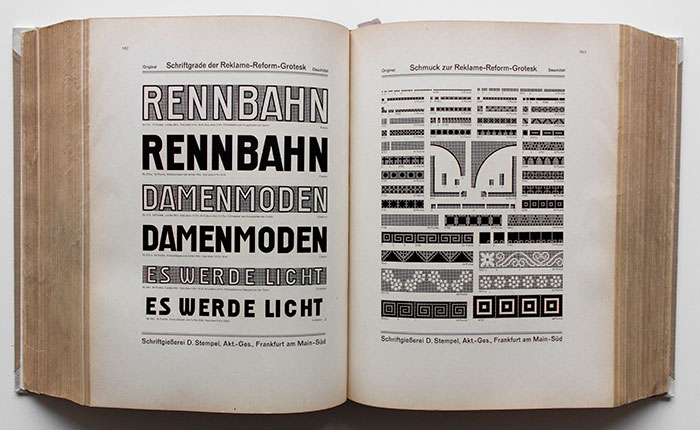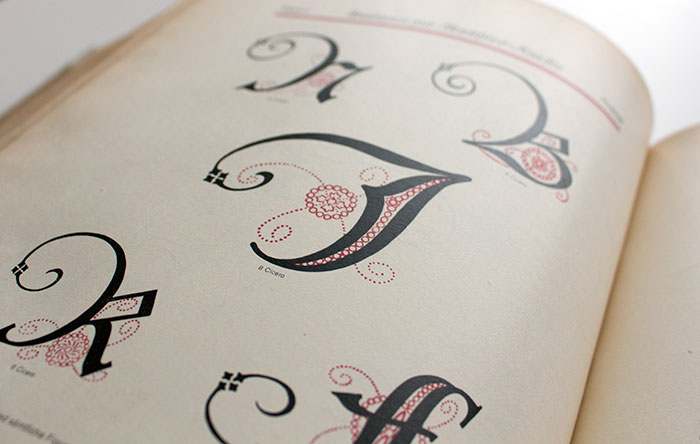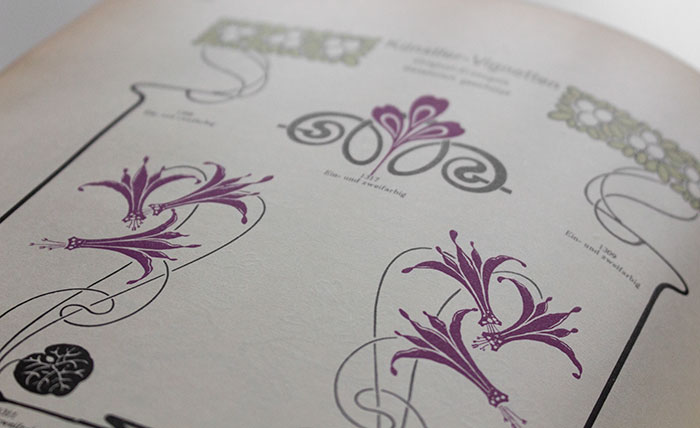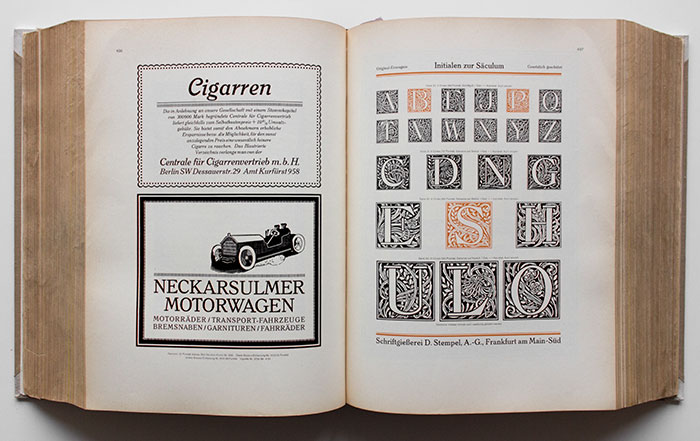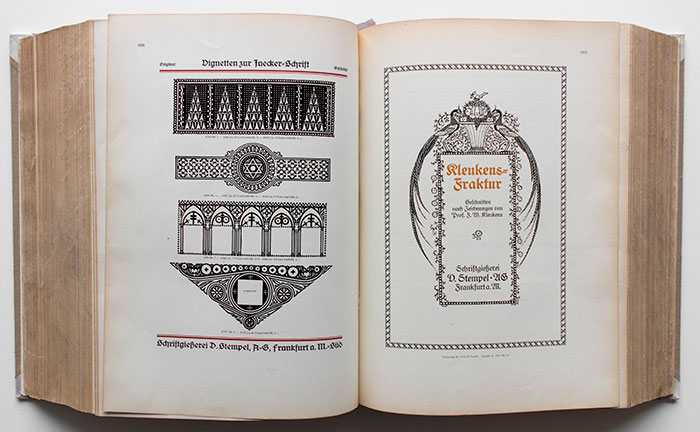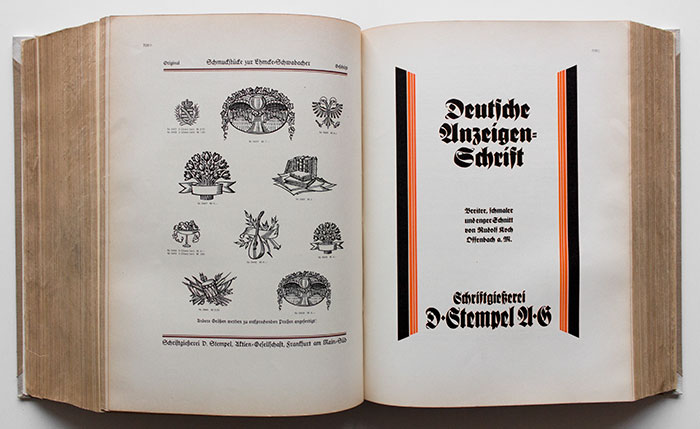
Das Ende des 19. Jahrhunderts von David Stempel gegründete Unternehmen wurde zu einer der bedeutendsten Schriftgießereien des 20. Jahrhunderts. 1925 gab das mittlerweile als Aktiengesellschaft firmierende Unternehmen eine circa 1500 Seiten starke Hauptprobe heraus. Sie ist eine der umfangreichsten Schriftproben überhaupt und ein einmaliges Spiegelbild der Typografie der Zeit. Neben häufig eingesetzten Bleisatz-Schriften zeigt die Probe auch die Einfassungen, Vignetten, Linien, Spezialziffern, Muster etc.
Inhaltsverzeichnis:
- Achilles-Fraktur
- Achilles-Fraktur, fette
- Achilles-Fraktur, halbfette
- Adler-Schreibmaschinenschrift
- Akzidenz-Gotisch, schmale
- Akzidenz-Schmuck
- Aldine, halbfette
- Aldine, schmale englische
- Altgotisch, Amerikanische
- Altgotisch, enge
- Altgotisch, Original-
- Altgotisch, Original-, Anwendung
- Alt-Schwabacher
- Alt-Schwabacher, Anwendung
- Amts-Antiqua
- Amts-Antiqua, Anwendung
- Amts-Antiqua, enge
- Amts-Antiqua, enge halbfette
- Amts-Antiqua, fette
- Amts-Antiqua, halbfette
- Amts-Fraktur
- Amts-Fraktur, Anwendung
- Amts-Fraktur, enge halbfette
- Amts-Fraktur, fette
- Amts-Fraktur, halbfette
- Amts-Fraktur-Initialen
- Amts-Fraktur, magere
- Amts-Fraktur, magere, Anwendung
- Amts-Fraktur, schmale fette
- Amts-Kursiv
- Amts-Kursiv, halbfette
- Amts-Kursiv, fette
- Amts-Schriften
- Amts-Schriften-ZIffern
- Ancienne
- Antike Elzevier
- Antike Elzevier, Anwendung
- Antike Skelett
- Antiqua-Brotschriften
- Antiqua, halbfette englische
- Antiqua, moderne fette
- Antiqua, Salon-
- Antiqua, Salon-, Anwendung
- Antiqua, schmale schlanke
- Antiqua, schmale halbfette
- Antiqua, schraffierte
- Anzeigenschrift
- Arabische Schriften
- Ariadne-Fraktur
- Ariadne-Fraktur, halbfette
- Aristokrat
- Aristokrat, Anwendung
- Armenische Schriften
- Arminius-Fraktur
- Arminius-Fraktur, halbfette
- Askpekten-Zeichen
- Astronomische Zeichen
- Assüree-Linien
- Assüree-Linien mit Wertzeichen und Firmenzeile
- Ausläufer für Messinglinien
- Auszeichnungsschriften für Brotschriften
- Barnum-Ornamente
- Baskerville, Original-, Anwendung
- Bek-Gran
- Bek-Gran-Einfassungen
- Bek-Gran-Einfassungen zweifarbig
- Bek-Gran, halbfette
- Bek-Gran-Initial-Verzierungen
- Bek-Gran-Kalender-Vignetten
- Bek-Gran-Schrift, Anwendung
- Bek-Gran-Umrahmungen
- Bek-Gran-Vignetten
- Bek-Gran, Werk-
- Berg- und Hüttenzeichen
- Bewegte Messinglinien mit Ecken
- Biedermeier-Reklame
- Biedermeier-Schmuck
- Blattstab, lichter und fetter
- Blumenschmuck Flora
- Blumenzauber-Einfassung
- Bogenregletten in Messing
- Börsenkurs-Schriften
- Börsenkurs-Schriften, Anwendung
- Börsenkurs-Zeichen
- Börsenkurs-Ziffern
- Bravour, Anwendung
- Bravour-Einfassung in Messing
- Bravour, fette
- Bravour, halbfette
- Bravour-Kursiv, fette
- Bravour-Kursiv, magere
- Bravour, magere
- Bravour, schmale fette
- Bravour, schmale magere
- Bravour-Schmuck
- Bravour, schraffierte
- Bravour, verzierte
- Bravour-Vignetten
- Bravour-Ziffern
- Breite Etienne
- Breite fette Egyptienne
- Breite fette Grotesk
- Breite Gotisch
- Breite Grotesk
- Breite fette Reform-Grotesk
- Breite fette Reform-Grotesk-Versalien
- Breite fette Renaissance
- Breite fette Salon-Grotesk
- Breite halbfette Reform-Grotesk
- Breite halbfette Reform-Grotesk-Versalien
- Breite halbfette Reform-Grotesk II
- Breite halbfette Reform-Grotesk II-Versalien
- Breite halbfette Renaissance
- Breite halbfette Salon-Grotesk
- Breite Inseraten-Reform-Grotesk
- Breite Inseraten-Reform-Grotesk-Versalien
- Breite Offenbacher Schwabacher
- Breite verzierte Italienne
- Breitkopf-Fraktur
- Breitkopf-Fraktur, Anwendung
- Breitkopf-Fraktur, halbfette
- Brotschriften, Kolonel mit großem Schriftbild
- Brotschriften, Insertio
- Brotschriften, Nonp. mit großem Schriftbild
- Brotschriften, Petit mit großem Schriftbild
- Bruchziffern
- Bruchziffern für Börsenkurse
- Buchgotisch
- Buchgotisch, Anwendung
- Buchgotisch, fette
- Buchgotisch, halbfette
- Buchgotisch, Initialen
- Buchgotisch, Schmuck
- Buhe-Fraktur
- Buhe-Fraktur, Anwendung
- Buhe-Fraktur, fette
- Buhe-Fraktur, fette, Anwendung
- Buhe-Fraktur, halbfette
- Buhe-Initialen
- Buhe-Schmuck
- Bürck-Linien
- Bürck-Schrift
- Bürck-Schrift, Anwendung
- Büxenstein-Antiqua
- Büxenstein-Antiqua, Anwendung
- Büxenstein-Antiqua, halbfette
- Büxenstein-Fraktur
- Büxenstein-Fraktur, Anwendung
- Büxenstein-Fraktur, halbfette
- Büxenstein-Kursiv
- Caslon-Gotisch
- Caslon-Gotisch, Anwendung
- Ceres-Fraktur
- Ceres-Fraktur, Anwendung
- Ceres-Fraktur, halbfette
- Christiansen-Einfassungen
- Christiansen-Intitialen
- Christiansen-Schrift
- Christiansen-Schrift, Anwendung
- Christiansen-Vignetten
- Clarendon
- Colonel-Brotschriften mit großem Schriftbild
- Continental
- Cyrillische Amts-Antiqua-Schriften
- Cyrillische Bravour-Schriften
- Cyrillische Holz-Schriften
- Cyrillische Karten-Schriften
- Cyrillische Reform-Grotesk-Schriften
- Cyrillische Römisch-Schriften
- Cyrillische Säculum-Schriften
- Cyrillische Schreibmaschinen-Schriften
- Damespiel-Figuren
- Danziger Antiqua
- Danziger Fraktur
- Danziger Fraktur, fette
- Delphin-Antiqua
- Delphin-Antiqua, halbfette
- Delphine-Kursiv
- Deutsche Anzeigenschrift, Anwendung
- Deutsche Anzeigenschrift, breiter Schnitt
- Deutsche Anzeigenschrift, enger Schnitt
- Deutsche Anzeigenschrift, Initialen
- Deutsche Anzeigenschrift, Schlußzeichen
- Deutsche Anzeigenschrift, schmaler Schnitt
- Deutsche Anzeigenschrift, Schwungbuchstaben
- Deutsche Handschreibschrift
- Deutsche Laufschrift
- Deutsche Laufschrift, Anwendung
- Deutsche Laufschrift, Endbuchstaben
- Deutsche Laufschrift-Initialen
- Deutsche Laufschrift, Zeilenfüller
- Deutsche Schreibschrift
- Deutsche Spielkartentypen
- Deutsche Zierschrift
- Diana
- Diana, Anwendung
- Diana, halbfette
- Didot-Antiqua
- Didot-Antiqua-, Anwendung
- Didot-Kursiv
- Dominospiel-Figuren
- Dreiviertelfette Reform-Grotesk
- Dreiviertefette Reform-Grotesk-Versalien
- Dutzend-Zeichen
- Egmont-Fraktur
- Egmont-Fraktur, Anwendung
- Egmont-Fraktur, fette
- Egmont-Fraktur, halbfette
- Egyptienne, breite fette
- Egyptienne-Kursiv, fette
- Egyptienne, magere enge
- Egyptienne, schmale
- Ehmcke-Fraktur
- Ehmcke-Fraktur, Anwendung
- Ehmcke-Fraktur, halbfette
- Ehmcke-Fraktur-Intitialen
- Ehmcke-Mediaeval
- Ehmcke-Medieaval, Anwendung
- Ehmcke-Mediaeval, halbfette
- Ehmcke-Mediaeval-Initialen
- Ehmcke-Mediaeval-Kursiv
- Ehmcke-Mediaeval-Schmuck
- Ehmcke-Mediaeval-Tabellen-Ziffern
- Ehmcke-Rustika
- Ehmcke-Rustika, Anwendung
- Ehmcke-Rustika-Initialen
- Ehmcke-Rustika-Schmuck
- Ehmcke-Schwabacher
- Ehmcke-Schwabacher, Anwendung
- Ehmcke-Schwabacher, halbfette
- Ehmcke-Schwabacher-Schmuck
- Ehmcke-Schwabacher-Schmuckstücke
- Ehmcke-Schwabacher-Zierbuchstaben
- Einfassung Herkules
- Einfassung Heureka
- Einfassung Immer fertig
- Einfassung Lätizia
- Einfassung Merkuria
- Einfassung Modern
- Einfassung Nestor
- Einfassung Non plus ultra
- Einfassung Orion
- Einfassung Propaganda
- Einfassung Serie 32
- Einfassung Serie 33
- Einfassung Serie 34
- Einfassung Serie 40
- Einfassung Serie 41
- Einfassung Serie 42
- Einfassung Serie 43
- Einfassung Serie 44
- Einfassung Serie 45
- Einfassung Serie 48
- Einfassung Serie 50
- Einfassung Serie 51
- Einfassung Solitair
- Einfassung Viktoria
- Einfassungen in Holz
- Einfassungen in Messing
- Einfassungen, mehrfarbige
- Einfassungen, Nachtrag zu den Reihen-
- Einfassungen, Reihen-
- Einfassungen zur Bek-Grau
- Einfassungen zur Bek-Grau, zweifarbig
- Einfassungen zur Bravour
- Einfassungen zur Buhe Fraktur
- Einfassungen zur Christiansen-Schrift
- Einfassungen zur Ehmcke-Mediaeval
- Einfassungen zur Ehmcke-Rustika
- Einfassungen zur Ehmcke-Schwabacher
- Einfassungen zur Frankfurt-Serie
- Einfassungen zur Gotischen Antiqua
- Einfassungen zur Helga-Antiqua
- Einfassungen zur Hölzl-Mediaeval
- Einfassungen zur Ingeborg-Antiqua
- Einfassungen zur Jaecker-Schrift
- Einfassungen zur Kleukens-Fraktur
- Einfassungen zur Matthies-Kursiv
- Einfassungen zur Reklame-Reform-Grotesk
- Einfassungen zur Sensation
- Einfassungs-Linien in Messing
- Einheits-Fraktur
- Ekkehard-Fraktur
- Ekkehard-Fraktur, Anwendung
- Ekkehard-Fraktur, halbfette
- Elegant
- Elegant, Anwendung
- Elfen-Fraktur
- Elfen-Fraktur, Anwendung
- Elfen-Fraktur-Initialen
- Elite-Kanzlei
- Elite-Kanzlei, Anwendung
- Elite, Zierschrift
- Elzevier, antike
- Elzevier, antike, Anwendung
- Endbuchstaben zur Deutschen Laufschrift
- Enge Altgotisch
- Enge Amts-Antiqua
- Enge Amts-Antiqua, Anwendung
- Enge Etienne
- Enge Etienne, Anwendung
- Enge fette Reform-Grotesk
- Enge fette Reform-Grotesk-Versalien
- Enge halbfette Reform-Grotesk
- Enge halbfette Reform-Grotesk-Versalien
- Enge halbfette Amts-Antiqua
- Enge halbfette Amts-Fraktur
- Enge Jaecker-Schrift
- Enge moderne Kanzlei
- Enge Normannia-Fraktur
- Enge Normannia-Fraktur, halbfette
- Enge magere Reform-Grotesk
- Enge magere Reform-Grotesk-Versalien
- Enge magere Säculum
- Enge Renaissance
- Englische Aldine, schmale
- Englische Antiqua, halbfette
- Englische Messinglinien
- Erator-Antiqua
- Erato-Kursiv
- Etienne, breite
- Etienne, enge
- Etienne, enge, Anwendung
- Etienne, freie
- Etienne, lichte
- Etienne, schmale fette
- Fahrplan-Anwendung
- Fahrplan-Material
- Fahrplan-Ziffern
- Fakturen-Zeihen
- Falstaff
- Faust-Fraktur
- Faust-Fraktur, Anwendung
- Faust-Fraktur, halbfette
- Faust-Fraktur, fette
- Faust-Fraktur, schmale halbfette
- Federzüge zur Jaecker-Schrift
- Fenella-Fraktur
- Fenella-Fraktur, Anwendung
- Fenelle-Fraktur, halbfette
- Feodora, Schreibschrift
- Fette Achilles-Fraktur
- Fette Amts-Antiqua
- Fette Amts-Fraktur
- Fette Amts-Kursiv
- Fette Antiqua, grobe Kolonel
- Fette Antiqua, grobe Petit
- Fette Antiqua, moderne
- Fette Bravour
- Fette Bravour-Kursiv
- Fette Buchgotisch
- Fette Buhe-Fraktur
- Fette Buhe-Fraktur, Anwendung
- Fette Ceres-Fraktur
- Fette Egmont-Fraktur
- Fette Egyptienne-Kursiv
- Fette Faust-Fraktur
- Fette Fraktur
- Fette Gotisch
- Fette Graziella
- Fette Grazielle, Anwendung
- Fette Gutenberg-Jubiläums-Fraktur
- Fette klassische Ornamente Serie 21
- Fette König-Antiqua
- Fette Kursiv
- Fette Normannia-Fraktur
- Fette Offenbacher Schwabacher
- Fette Reform-Grotesk
- Fette Reform-Grotesk-Versalien
- Fette Reform-Grotesk-Kursiv
- Fette Reform-Grotesk-Kursiv-Versalien
- Fette Regina-Kursiv
- Fette Regina-Kursiv, Anwendung
- Fette Säculum
- Fette Schiller-Jubiläumsschrift
- Fette Schiller-Jubiläumsschrift, Anwendung
- Fette Schwabacher
- Fette Sensation
- Fette Teutonia
- Fette Torpedo
- Fette Undine
- Fetter Blattstab
- Fortschritt-Schmuck
- Fraktur-Brotschriften
- Fraktur, fette
- Fraktur, halbfette
- Fraktur-Initialen
- Fraktur-Initialen, kräftige
- Fraktur, schmale halbfette
- Frankfurt-Schrift, Anwendung
- Frankfurt-Serie I
- Frankfurt-Serie II
- Frankfurt-Serie I und II, Anwendung
- Frankfurt-Serie, Initialen zur
- Frankfurt-Serie, Kopfleisten zur
- Frankfurt-Serie, Ornamente zur
- Frankfurter Schwabacher
- Frankfurter Schwabacher, halbfette
- Französische Spielkartentypen
- Freie Etienne
- Freie Grotesk I
- Freie Grotesk II
- Freie Initialen zur Kleukens-Fraktur
- Freie Korso-Versalien
- Freie Ornamente, moderne
- Freie Romanisch
- Freie Versalien zur Kleukens-Fraktur
- Freie Versalien zur Matthias-Kursiv
- Freie Versalien zur Ratio-Latein
- Fröbel-Fraktur
- Fröbel-Fraktur, halbfette
- Frühling
- Garamond-Antiqua, Anwendung
- Germinal
- Gewichtszeichen
- Gotische Antiqua
- Gotische Antiqua, Anwendung
- Gotische Antiqua-Einfassungen
- Gotische Antiqua-Initialen
- Gotisch, breite
- Gotisch, Caslon
- Gotisch, fette
- Gotisch, Kaiser-
- Gotisch, Morris-
- Gotisch, schmale Akzidenz
- Gotisch, schmale halbfette
- Graphik
- Graziella, Anwendung
- Graziella, fette
- Graziella, magere
- Graziella, schmale fette
- Gretchen-Einfassung
- Griechische Schriften
- Grotesk, breite
- Grotesk, breite fette
- Grotesk, breite fette Salon-
- Grotesk, breite halbfette Salon-
- Grotesk, halbfette Kursiv-
- Grotesk, Handels-
- Grotesk, Handels-, Anwendung
- Grotesk I und II, freie
- Grotesk, Inseraten-
- Grotesk, magere schlanke
- Grotesk, Mediaeval-
- Grotesk, neue schlanke
- Grotesk, Reform, siehe Reform-Grotesk
- Grotesk, Siegfried-
- Grotesk, schlanke
- Grotesk, schmale enge
- Grotesk, schmale halbfette
- Gutenberg-Fraktur
- Gutenberg-Jubiläums-Fraktur
- Gutenberg-Jubiläums-Fraktur, Anwendung
- Gutenberg-Jubiläums-Fraktur, fette
- Gutenberg-Jubiläums-Fraktur, halbfette
- Halbfette Achilles-Fraktur
- Halbfette Aldine
- Halbfette Amts-Antiqua
- Halbfette Amts-Fraktur
- Halbfette Amts-Kursiv
- Halbfette Arminus-Fraktur
- Halbfette Ariadne-Fraktur
- Halbfette Bek-Gran
- Halbfette Bravour
- Halbfette Breitkopf-Fraktur
- Halbfette Buhe-Fraktur
- Halbfette Buchgotisch
- Halbfette Büxenstein-Antiqua
- Halbfette Büxenstein-Fraktur
- Halbfette Ceres-Fraktur
- Halbfette Danziger-Fraktur
- Halbfette Delphin-Antiqua
- Halbfette Diana
- Halbfette englische Antiqua
- Halbfette Egmont-Fraktur
- Halbfette Ehmcke-Fraktur
- Halbfette Ehmcke-Mediaeval
- Halbfette Ehmcke-Schwabacher
- Halbfette Ekkehard-Fraktur
- Halbfette Faust-Fraktur
- Halbfette Fenelle-Fraktur
- Halbfette Fraktur
- Halbfette Frankfurter Schwabacher
- Halbfette Fröbel-Fraktur
- Halbfette Gutenberg-Jubiläums-Fraktur
- Halbfette Heinz-König-Setzmaschinen-Fraktur
- Halbfette Helga-Antiqua
- Halbfette Helvetia
- Halbfette Holländische Antiqua
- Halbfette Holzhausen-Antiqua
- Halbfette Hölzl-Mediaeval
- Halbfette Ingeborg-Antiqua
- Halbfette Jaecker-Schrift
- Halbfette Kanzlei
- Halbfette Kleukens-Fraktur
- Halbfette Kursiv
- Halbfette Kursiv-Grotesk
- Halbfette Künstlerschrift
- Halbfette Künstler-Schreibschrift
- Halbfette Labor-Antiqua
- Halbfette Marius-Fraktur
- Halbfette Mediaeval I
- Halbfette Medieaval I, Anwendung
- Halbfette Mediaeval II
- Halbfette Mediaeval-Schreibschrift
- Halbfette Merkur
- Halbfette moderne Schwabacher
- Halbfette Neuklassisch
- Halbfette Neuzeit-Antiqua
- Halbfette Neuzeit-Fraktur
- Halbfette Normannia-Fraktur
- Halbfette Offenbacher Schwabacher
- Halbfette Perfekt
- Halbfette Perikles-Antiqua
- Halbfette Ratio-Latein
- Halbfette Reform-Antiqua
- Halbfette Reform-Fraktur
- Halbfette Reform-Grotesk
- Halbfette Reform-Grotesk-Versalien
- Halbfette Reform-Grotesk-Kursiv
- Halbfette Reform-Grotesk-Kursiv-Versalien
- Halbfette Renaissance
- Halbfette Romanisch
- Halbfette Romanisch-Kursiv
- Halbfette Romeo-Fraktur
- Halbfette Romulus-Fraktur
- Halbfette Römisch
- Halbfette Römisch-Kursiv
- Halbfette Säculum
- Halbfette Säculum-Kursiv
- Halbfette Schreibschrift
- Halbfette Schwabacher
- Halbfette Setzmaschinen-Mediaeval
- Halbfette Setzmaschinen-Romanisch
- Halbfette Städel-Antiqua
- Halbfette Stempel-Fraktur
- Halbfette Turnus-Antiqua
- Halbfette Union
- Halbfette Weißflog-Antiqua
- Halbfette Wiener Antiqua
- Handels-Antiqua
- Handels-Grotesk
- Handels-Grotesk, Anwendung
- Handschreibschrift, deutsche
- Handschreibschrift, lateinische
- Hände
- Hände in Holz
- Hände in Messing
- Hebräische Schriften
- Heinz König-Setzmaschinen-Fraktur
- Heinz König-Setzmaschinen-Fraktur, Andwendung
- Heinz König-Setzmaschinen-Fraktur, halbfette
- Helga-Antiqua
- Helga-Antiqua, Anwendung
- Helga-Antiqua, halbfette
- Helga-Einfassungen
- Helga-Initialen
- Helga-Kursiv
- Helga-Vignetten
- Helvetia, halbfette
- Helvetia, magere
- Herkules-Einfassung
- Herold
- Heureka-Einfassung
- Holländische Antiqua
- Holländische Antiqua, halbfette
- Holländische Antiqua-Initialen
- Holländische Kursiv
- Holzhausen-Antiqua
- Holzhausen-Antiqua, Anwendung
- Holzhausen-Antiqua, halbfette
- Holzhausen-Kursiv
- Holzschriften
- Hölzl-Medieaeval, Anwendung
- Hölzl-Medieaeval, halbfette
- Hölzl-Medieaeval-Initialen
- Hölzl-Medieaeval-Kursiv
- Hölzl-Medieaeval-Ornamente
- Hölzl-Medieaeval-Vignetten
- Hölzl-Medieaeval-Ziffern
- Hubertus-Fraktur, I. und II. Garnitur
- Hütten-Zeichen
- Immer fertig, Einfassung
- Ingeborg-Antiqua
- Ingeborg-Antiqua, Anwendung
- Ingeborg-Antiqua, halbfette
- Ingeborg-Antiqua-Ziffern
- Ingeborg-Initialen
- Ingeborg-Kursiv
- Ingeborg-Ornamente
- Ingeborg-Vignetten
- Initial-Kassetten zur Matthies-Kursiv
- Initial-Verzierungen zur Bek-Gran
- Initialen, Fraktur-
- Initialen, kräftige Fraktur-
- Initialen zur Amts-Fraktur
- Initialen zur Buhe-Fraktur
- Initialen zur Buchgotisch
- Initialen zur Christiansen-Schrift
- Initialen zur Deutschen Anzeigenschrift
- Initialen zur Deutschen Laufschrift
- Initialen zur Ehmcke-Fraktur
- Initialen zur Ehmcke-Mediaeval
- Initialen zur Ehmcke-Rustika
- Initialen zur Ehmcke-Schwabacher
- Initialen zur Elfen-Fraktur
- Initialen zur Frankfurt-Serie
- Initialen zur Gotischen Antiqua
- Initialen zur Helga-Antiqua
- Initialen zur Holländischen Antiqua
- Initialen zur Hölzl-Mediaeval
- Initialen zur Ingeborg-Antiqua
- Initialen zur Jaecker-Schrift
- Initialen zur Kleukens-Fraktur
- Initialen zur Künstlerschrift
- Initialen zur Matthies-Kursiv
- Initialen zur modernen Schwabacher
- Initialen zur Morris-Gotisch
- Initialen zur Neuzeit-Antiqua
- Initialen zur Neuzeit-Fraktur
- Initialen zur Ratio-Latein
- Initialen zur Romanisch
- Initialen zur Säculum
- Initialen zur Sensation
- Initialen zur Stempel-Fraktur
- Initialen zur Teutonia
- Inserat-Einfassungen für Handel und Gewerbe
- Inseraten-Grotesk
- Inseraten-Reform-Grotesk-Kursiv
- Inseraten-Reform-Grotesk-Kursiv-Versalien
- Insertio-Schriften
- Isabella
- Italienne
- Italienne, breite verzierte
- Italienne, Skelett-
- Italienne, verzierte
- Integral-Zeichen
- Jaecker-Initialen
- Jaecker-Ornamente
- Jaecker-Schrift
- Jaecker-Schriftn, Anwendung
- Jaecker-Schrift, enge
- Jaecker-Schrift, halbfette
- Jaecker-Schrift, magere
- Jaecker-Schrift, magere, Anwendung
- Jaecker-Vignetten
- Jaecker-Zierat
- Janson-Antiqua
- Janson-Antiqua, Anwendung
- Janson-Kursiv
- Kaiser-Gotisch
- Kalender-Vignetten, Bek-Gran
- Kalender-Ziffern
- Kalender-Ziffern in Holz
- Kanzlei, brei
- Kanzlei, Elite-
- Kanzlei, Elite-, Anwendung
- Kanzlei, enge moderne
- Kanzlei, halbfette
- Kanzlei, Viktoria-
- Kapitälchen zur Säculum
- Kapitälchen zur Weißfloß-Antiqua
- Karolus-Fraktur
- Kartographische Zeichen
- Kassetten in Messing
- Katalog-Ziffern
- Klammern in Messing
- Klassische Ornamente Serie 21, fette
- Klassische Ornamente Serie 22
- Kleukens-Fraktur
- Kleukens-Fraktur, Anwendung
- Kleukens-Fraktur, frei Initialen
- Kleukens-Fraktur, freie Versalien
- Kleukens-Fraktur, halbfette
- Kleukens-Fraktur-Initialen
- Kleukens-Fraktur-Ornamente
- Kleukens-Vignetten
- Kolli-Zeichen
- Kolonel-Brotschriften mit großem Schriftbild
- Kolumnentitel in Messing
- Kombinationsschmuck in Messing
- Kontrast-Ornamente
- König-Antiqua
- König-Antiqua, fette
- Kopfleisten zur Frankfurt-Serie
- Kopfleisten zur Säculum
- Korrespondenz-Zeichen
- Korso
- Korso, Anwendung
- Korso, freie Versalien
- Korso-Ornamente
- Kräftige Fraktur-Initialen
- Kreise in Messing
- Kreuze
- Kreuze in Messing
- Kronen
- Kursiv, fette
- Kursiv, halbfette
- Kursiv-Grotesk, halbfette
- Kursiv-Rundschrift
- Künstler-Reform-Grotesk
- Künstlerschrift, halbfette
- Künstlerschrift-Initialen
- Künstlerschrift, lichte
- Künstlerschrift, magere
- Künstlerschrift Wodan, schmale fette
- Künstlerschrift Wodan, schmale fette, Anwendung
- Künstler-Schreibschrift
- Künstler-Schreibschrift, Anwendung
- Künstler-Schreibschrift, halbfette
- Künstler-Schreibschrift, schmale
- Künstler-Schreibschrift, schmale, Anwendung
- Künstler-Linien Serie 1
- Künstler-Linien Serie 2
- Künstler-Linien Serie 3
- Künstler-Linien Serie 4
- Künstler-Linien Serie 5
- Künstler-Linien Serie 6
- Künstler-Linien Serie 7
- Künstler-Linien Serie 8, lichte
- Künstler-Linien Serie 9
- Künstler-Linien Serie 10
- Künstler-Linien Serie 11, lichte
- Künstler-Linien Serie 12
- Künstler-Linien Serie 13
- Künstler-Vignetten
- Labor-Antiqua, Anwendung
- Labor-Antiqua, halbfette
- Lateinische Handschreibschrift
- Lätizia-Einfassung
- Libelle, Renaissance-Schrift
- Libelle, Renaissance-Schrift, Anwendung
- Lichte Etienne
- Lichte Künstlerschrift
- Lichte Künstlerlinien Serie 8
- Lichte Künstlerlinien Serie 11
- Lichte Mignon
- Lichte Ratio-Versalien
- Lichte Reform-Grotesk
- Lichte Romanisch
- Lichte schmale Renaissance
- Lichte schmale Renaissance, Anwendung
- Lichte Torpedo
- Lichte Wodan
- Lichter Blattstab
- Linien-Ausläufer in Messing
- Lithographia
- Lithographia II
- Lithographia-Versalien II
- Liturgisch
- Lotterie-Ziffern
- Luthersche Fraktur
- Luthersche Fraktur, Anwendung
- Magere Amts-Fraktur
- Magere Bravour
- Magere Bravour-Kursiv
- Magere enge Egyptienne
- Magere Graziella
- Magere Graziella, Anwendung
- Magere Helvetia
- Magere Jaecker-Schrift
- Magere Jaecker-Schrift, Anwendung
- Magere Künstlerschrift
- Magere moderne Reklame
- Magere Reform-Grotesk
- Magere Reform-Grotesk-Versalien
- Magere Reform-Grotesk-Kursiv
- Magere Reform-Grotesk-Kursiv-Versalien
- Magere Regina-Kursiv
- Magere Regina-Kursiv, Anwendung
- Magere Römisch
- Magere Römisch, Anwendung
- Magere Säculum
- Magere Schiller-Jubiläumsschrift
- Magere Schiller-Jubiläumsschrift, Anwendung
- Magere schlanke Grotesk
- Magere Undine
- Magnet
- Marie Antoinette
- Marie Antoinette, Anwendung
- Marius-Fraktur
- Marius-Fraktur, halbfette
- Mathematische Zeichen
- Matthies-Kursiv
- Matthies-Kursiv, Anwendung
- Matthies-Kursiv-Einfassungen
- Matthies-Kursiv, freie Versalien
- Matthies-Kursiv-Initialen und Initial-Kass.
- Matthies-Kursiv-Vignetten
- Maysche Fraktur I. und II. Garnitur
- Mediaeval-Grotesk
- Mediaeval I
- Mediaeval I, halbfette
- Mediaeval I, halbfette, Anwendung
- Mediaeval I, Setzmaschinen-
- Mediaeval I, Setzmaschinen-, halbfette
- Mediaeval II
- Mediaeval II, halbfette
- Mediaeval-Kursiv I
- Mediaeval-Kursiv I, Setzmaschinen-
- Mediaeval-Kursiv II
- Mediaeval, schattierte
- Mediaeval-Schreibschrift
- Mediaeval-Schreibschrift, halbfette
- Mehrfarbige Einfassungen
- Merkur
- Merkur, halbfette
- Merkuria-Einfassung
- Messing-Assüree-Linien
- Messing-Bogenregletten
- Messing-Ecken und -Mittelstücke
- Messing-Ecken, verzierte
- Messing-Einfassung Kosmos
- Messing-Einfassung Non plus ultra
- Messing-Einfassung Stabil
- Messing-Einfassungen
- Messing-Einfassungs-Linien
- Messing-Hände
- Messing-Kassetten
- Messing-Klammern
- Messing-Kolumnentitel
- Messing-Kombinations-Schmuck
- Messing-Kreise
- Messing-Kreuze
- Messing-Linien
- Messing-Linien-Ausläufer
- Messing-Linien, bewegte, mit Ecken
- Messing-Linien, englische
- Messing-Linien, Universal-
- Messing-Moiré-Linien
- Messing-Negative
- Messing-Ovale
- Messing-Pfeile
- Messing-Rubrikzeichen
- Messing-Schlußlinien
- Messing-Spaltenlinien und -Facetten
- Messing-Trauerränder
- Meteorologische Zeichen
- Metrische Zeichen
- Mignon, lichte
- Mithras-Schmuckserie
- Moderne freie Ornamente
- Moderne Plakat-Einfassung
- Moderne Reihen-Einfassungen
- Moderne Reklame
- Moderne Reklame, magere
- Moderne Schwabacher
- Moderne Schwabacher, halbfette
- Moderne Schwabacher-Initialen
- Moderne Vignetten für Prospekte, Inserate etc.
- Moiré-Linien
- Mondphasen
- Monogramme
- Morris-Gotisch
- Morris-Gotisch-Initialen
- Naturwissenschaftliche Zeichen
- Negative in Messing
- Nestor-Einfassung
- Neue Inserat-Einfass. für Hand und Gewerbe
- Neue schlanke Grotesk
- Neue zarte Säculum
- Neue zarte Säculum, Anwendung
- Neue zarte Säculum-Kursiv
- Neueste Schreibschrift
- Neuklassisch
- Neuklassisch, Anwendung
- Neuklassisch, halbfette
- Neuklassisch-Kursiv
- Neuzeit-Antiqua
- Neuzeit-Fraktur, Anwendung
- Neuzeit-Fraktur, halbfette
- Neuzeit-Fraktur-Initialen
- Neuzeit-Initialen
- Neuzeit-Kursiv
- Neuzeit-Zirkular
- Non plus ultra-Einfassung
- Nonpareille-Brotschriften mit großem Schriftbild
- Normalbreite fette Reform-Grotesk
- Normalbreite fette Reform-Grotesk-Versalien
- Normalbreite halbfette Reform-Grotesk
- Normalbreite halbfette Reform-Grotesk-Versalien
- Normalbreite Inseraten-Reform-Grotesk
- Normalbreite Inseraten-Reform-Grotesk-Versalien
- Normalbreite magere Reform-Grotesk
- Normalbreite magere Reform-Grotesk-Versalien
- Normannia-Fraktur
- Normannia-Fraktur, enge
- Normannia-Fraktur, enge halbfette
- Normannia-Fraktur, fette
- Normannia-Fraktur, halbfette
- Normen-Reform-Grotesk-Kursiv
- Normen-Reform-Grotesk-Kursiv-Versalien
- Notenlinien
- Numismatische Zeichen
- Nummern-Zeichen
- Offfenbacher Schwabacher
- Offfenbacher Schwabacher, Anwendung
- Offfenbacher Schwabacher, breite
- Offfenbacher Schwabacher, fette
- Offfenbacher Schwabacher, halbfette
- Offfenbacher Schwabacher, schmale halbfette
- Ordenszeichen
- Orientalische Schriften
- Original-Altgotisch
- Original-Altgotisch, Anwendung
- Original-Baskerville, Anwendung
- Orion-Einfassung
- Ornamentale Verzierungen von Heinz Keune
- Ornamente zur Frankfurt-Serie
- Ornamente zur Hölzl-Mediaeval
- Ornamente zur Ingeborg-Antiqua
- Ornamente zur Jaecker-Schrift
- Ornamente zur Kleukens-Fraktur
- Ornamente zur Korso
- Orientalischer Schmuck
- Ovale in Messing
- Parzival-Schmuck
- Patriotische Einfassung
- Patriotischer Schmuck
- Perfekt
- Perfekt, halbfette
- Perikles-Antiqua
- Perikles, Antiqua, halbfette
- Perikles-Kursiv
- Petit-Brotschriften mit großem Schriftbild
- Pfeile in Holz
- Pfeile Messing
- Pflanzen-Einfassung
- Phantasie-Ornamente
- Pinsel-Grotesk
- Plakat-Schriften in Holz
- Plakat-Schrift Simson, in Holz
- Planeten-Zeichen
- Pluto
- Polo
- Preciosa
- Propaganda
- Propaganda-Einfassung
- Propaganda-Romanisch
- Propaganda-Romanisch, Anwendung
- Ranken-Einfassung
- Ratio-Initialen
- Ratio-Kursiv
- Ratio-Latein
- Ratio-Latein, Anwendung
- Ratio-Latein, freie Versalien
- Ratio-Latein, halbfette
- Ratio-Latein-Ziffern
- Ratio-Versalien, lichte
- Rautendelein-Einfassung
- Rebe, Wein-Einfassung
- Reform-Antiqua
- Reform-Antiqua, Anwendung
- Reform-Antiqua, halbfette
- Reform-Fraktur
- Reform-Fraktur, Anwendung
- Reform-Fraktur, halbfette
- Reform-Grotesk, Anwendung
- Reform-Grotesk, breite fette
- Reform-Grotesk, breite halbfette
- Reform-Grotesk, breite Inseraten-
- Reform-Grotesk, breite magere
- Reform-Grotesk, dreiviertelfette
- Reform-Grotesk, enge fette
- Reform-Grotesk, enge halbfette
- Reform-Grotesk, enge magere
- Reform-Grotesk, fette
- Reform-Grotesk, halbfette
- Reform-Grotesk, lichte
- Reform-Grotesk, magere
- Reform-Grotesk, normalbreite fette
- Reform-Grotesk, normalbreite halbfette
- Reform-Grotesk, normalbreite Inseraten-
- Reform-Grotesk, normalbreite magere
- Reform-Grotesk, schmale fette
- Reform-Grotesk, umstochene
- Reform-Grotesk II, breite halbfette
- Reform-Grotesk II-Versalien, breite halbfette
- Reform-Grotesk, Künstler-
- Reform-Grotesk-Kursiv, fette
- Reform-Grotesk-Kursiv, halbfette
- Reform-Grotesk-Kursiv. Inseraten-
- Reform-Grotesk-Kursiv, magere
- Reform-Grotesk-Kursiv, Normen-
- Reform-Grotesk-Kursiv-Versalien, fette
- Reform-Grotesk-Kursiv-Versalien, halbfette
- Reform-Grotesk-Kursiv-Versalien, Inseraten-
- Reform-Grotesk-Kursiv-Versalien, magere
- Reform-Grotesk-Kursiv-Versalien, Normen-
- Reform-Grotesk, Reklame-
- Reform-Grotesk, Schmuck zur Reklame-
- Reform-Grotesk-Versalien, breite fette
- Reform-Grotesk-Versalien, breite halbfette
- Reform-Grotesk-Versalien, breite Inseraten-
- Reform-Grotesk-Versalien, breite magere
- Reform-Grotesk-Versalien, dreiviertelfette
- Reform-Grotesk-Versalien, enge fette
- Reform-Grotesk-Versalien, enge halbfette
- Reform-Grotesk-Versalien, enge magere
- Reform-Grotesk-Versalien, fette
- Reform-Grotesk-Versalien, halbfette
- Reform-Grotesk-Versalien, magere
- Reform-Grotesk-Versalien, normalbreite fette
- Reform-Grotesk-Versalien, normalbreite halbfette
- Reform-Grotesk-Versalien, normalbreite Inseraten-
- Reform-Grotesk-Versalien, normalbreite magere
- Reform-Grotesk-Versalien, schmale fette
- Reform-Grotesk-Ziffern
- Reform-Kursiv
- Regina-Kursiv, Anwendung
- Regina-Kursiv, fette
- Regina-Kursiv, magere
- Reihen-Einfassungen
- Reihen-Einfassungen, mehrfarbige
- Reihen-Einfassungen, Nachtrag
- Reklame, Biedermeier-
- Reklame-Einfassung Sensation
- Reklame-Einfassung Serie 23
- Reklame-Kursiv
- Reklame, magere moderne
- Reklame, moderde
- Reklame-Reform-Grotesk
- Reklame-Reform-Grotesk-Schmuck
- Renaissance, enge
- Renaissance, halbfette
- Renaissance, lichte schmale
- Renaissance, lichte schmale Anwendung
- Renaissance, schmale halbfette
- Renaissance-Schrift Libelle
- Renaissance-Schrift Libelle, Anwendung
- Romanisch, freie
- Romanisch, halbfette
- Romanisch, lichte
- Romanisch-Kursiv, halbfette
- Romanisch No. 1, Setzmaschinen-
- Romanisch No. 2, Setzmaschinen-
- Romanisch, schmale halbfette
- Romanische Antiqua
- Romanische Initialen
- Romanische Kursiv
- Romeo-Fraktur
- Romeo-Fraktur, halbfette
- Romulus-Frakur
- Romulus-Fraktur, halbfette
- Rosetten
- Römisch, Anwendung
- Römisch-Kursiv
- Römisch-Kursiv, halbfette
- Römisch, magere
- Rubin-Antiqua
- Rubin-Kursiv
- Rubrikzeilen in Messing
- Rundschrift
- Rundschrift, Kursiv-
- Runen-Schrift
- Russische Schriften
- Russische Schriften in Holz
- Salon-Antiqua
- Salon-Antiqua, Anwendung
- Salon-Grotesk, breite fette
- Salon-Grotesk, breite halbfette
- Säculum, Anwendung
- Säculum-Bruchziffern
- Säculum, enge magere
- Säculum, fette
- Säculum, halbfette
- Säculum-Initialen
- Säculum-Kapitälchen
- Säculum-Kopfleisten
- Säculum-Kursiv
- Säculum-Kursiv, halbfette
- Säculum-Kursiv, neue zarte
- Säculum, magere
- Säculum, neue zarte
- Säculum, schmale halbfette
- Säculum, Zirkular-
- Säculum-Ziffern
- Saltaspiel-Figuren
- Saxonia-Einfassung
- Scripts
- Senckenberg-Antiqua
- Senckenberg-Egyptienne
- Sensation
- Sensation, Anwendung
- Sensation, Einfassungen und Zierstücke
- Sensation, fette
- Sensation, Initialen
- Sensation, schmalfette
- Serena
- Serien-Einfassung:
- Serie 23, Reklame-Einfassung
- Serie 33
- Serie 34
- Serie 40
- Serie 41
- Serie 42
- Serie 43
- Serie 44
- Serie 45
- Serie 48
- Serie 50
- Serie 51
- Serie 20036, Wein-Einfassung
- Serien-Einfassungen
- Setzmaschinen-Fraktur, Heinz König-
- Setzmaschinen-Fraktur, Heinz König-, Anwendung
- Setzmaschinen-Medieaval I
- Setzmaschinen-Medieaval, Anwendung
- Setzmaschinen-Medieaval-Kursiv I
- Setzmaschinen-Romanisch-Kursiv Nr. 1 und 2
- Setzmaschinen-Romanisch Nr. 1
- Setzmaschinen-Romanisch Nr. 2
- Setzmaschinen-Romanisch Nr. 1 und 2, halbfette
- Siegfried-Grotesk
- Silberschrift
- Silhouetten-Einfassung
- Simson, Plakatschrift
- Skelett, antike
- Skelett-Italienne
- Solitair-Einfassung
- Spaltenlinien in Messing und Messing-Facetten
- Spielkartentypen, Deutsche
- Spielkartentypen, Französische
- Schachfiguren
- Stattierte Medieaval
- Schiller-Jubiläumsschrift, Anwendung
- Schiller-Jubiläumsschrift, fette
- Schiller-Jubiläumsschrift, magere
- Schiler-Schmuck
- Schlanke Grotesk
- Schlanke Grotesk, magere
- Schlanke Grotesk, neue
- Schlanke schmale Antiqua
- Schlußzeichen zur Deutschen Anzeigenschrift
- Schlußlinien in Holz
- Schlußlinien in Messing
- Schmale Akzidenz-Gotisch
- Schmale Egyptienne
- Schmale enge Grotesk
- Schmale englische Aldine
- Schmale fette Amts-Fraktur
- Schmale fette Bravour
- Schmale fette Etienne
- Schmale fette Graziella
- Schmale fette Graziella, Anwendung
- Schmale fette Künstlerschrift Wodan
- Schmale fette Künstlerschrift Wodan, Anwendung
- Schmale fette Reform-Grotesk
- Schmale fette Reform-Grotesk-Versalien
- Schmale halbfette Antiqua
- Schmale halbfette Faust-Fraktur
- Schmale halbfette Fraktur
- Schmale halbfette Gotisch
- Schmale halbfette Grotesk
- Schmale halbfette Offenbacher Schwabacher
- Schmale halbfette Renaissance
- Schmale halbfette Säculum
- Schmale magere Bravour
- Schmale Künstler-Schreibschrift
- Schmale Künstler-Schreibschrift, Anwendung
- Schmale Renaissance, lichte
- Schmale Renaissance, lichte, Anwendung
- Schmalfette Sensation
- Schmuck zur Buchgotisch
- Schmuck zur Buhe-Fraktur
- Schmuck zur Bravour
- Schmuck zur Ehmcke-Mediaeval
- Schmuck zur Ehmcke-Rustika
- Schmuck zur Ehmcke-Schwabacher
- Schmuck zur Jaecker-Schrift
- Schmuck zur Reklame-Reform-Grotesk
- Schmuckserie Mithras
- Schmuckstücke in Holz
- Schmuckstücke zur Ehmcke-Schwabacher
- Schneekönigin
- Schraffierte Antiqua
- Schraffiert Bravour
- Schreibmaschinen-Schriften
- Schreibmaschinen-Schriften, Anwendung
- Schreibschrift, deutsche
- Schreibschrift, deutsche Hand-
- Schreibschrift Feodora
- Schreibschrift, halbfette
- Schreibschrift, halbfette Künstler-
- Schreibschrift, halbfette Medieaval-
- Schreibschrift, Künstler-
- Schreibschrift, Künstler-, Anwendung
- Schreibschrift, lateinische Hand-
- Schreibschrift, Mediaeval-
- Schreibschrift, neueste
- Schreibschrift, schmale Künstler-
- Schreibschrift, schmale Künstler-, Anwendung
- Schriften für Börsenkurse
- Schriften für Börsenkurse, Anwendung
- Schuhmachersche Fraktur
- Schwabacher
- Schwabacher, Alt-
- Schwabacher, Alt-, Anwendung
- Schwabacher, breite Offenbacher
- Schwabacher, fette
- Schwabacher, fette Offenbacher
- Schwabacher, Frankfurter
- Schwabacher, halbfette
- Schwabacher, halbfette Frankfurter
- Schwabacher, halbfette moderne
- Schwabacher, halbfette Offenbacher
- Schwabacher-Initialen, moderne
- Schwabacher, moderne
- Schwabacher, Offenbacher
- Schwabacher, Offenbacher, Anwendung
- Schwabacher, schmale halbfette Offenbacher
- Schwungbuchstaben zur Deutschen Anzeigenschrift
- Städel-Antiqua
- Städel-Antiqua, Anwendung
- Städel-Antiqua, halbfette
- Städel-Kursiv
- Stempel-Fraktur
- Stempel-Fraktur, Anwendung
- Stempel-Fraktur, halbfette
- Stempel-Fraktur, Initialen
- Sterne
- Stilisierte Astern
- Stilisierte Schwertlilien
- Stumpffeine Ornamente
- Tasso
- Teutonia
- Teutonia, Anwendung
- Teutonia-Fraktur, 1. und 2. Garnitur
- Teutonia, fette
- Teutonia-Initialen
- Tierkreiszeichen
- Torpedo
- Torpedo, Anwendung
- Torpedo, fette
- Torpedo, lichte
- Torpedo, zweifarbige
- Torpedo, Zirkular-
- Trauerränder in Messing
- Trifolium-Bordüre
- Turnus-Antiqua mit Halbfetter und Kursiv
- Umrahmungen zur Bek-Gran
- Umstochene Reform-Grotesk
- Undine, fette
- Undine, magere
- Unger-Fraktur
- Unger-Fraktur, Anwendung
- Union
- Union, Anwendung
- Union, halbfette
- Union-Kursiv
- Universal-Messing-Linien
- Universal-Ornamente Serie 20
- Universal-Zierat
- Untergrund
- Urdu
- Vereins-Einfassung
- Vereinszeichen
- Verschiedene Zeichen
- Verzierte Bravour
- Verzierte Italienne
- Verzierte Italienne, breite
- Verzierte Messing-Ecken
- Verzierungen, ornamentale, von Heinz Keune
- Vignetten in Holz
- Vignetten, Künstler-
- Vignetten, moderne, für Prospekte, Inserate etc.
- Vignetten zur Bek-Gran
- Vignetten zur Bravour
- Vignetten zur Christiansen-Schrift
- Vignetten zur Ehmcke-Schwabacher
- Vignetten zur Hölzl-Mediaeval
- Vignetten zur Ingeborg-Antiqua
- Vignetten zur Jaecker-Schrift
- Vignetten zur Matthies-Kursiv
- Vignetten von Prof. F. E. Ehmcke
- Vignetten von Prof. F. W. Kleukens
- Viktoria-Einfassung
- Viktoria-Kanzlei
- Visite
- Vorsatzmuster
- Washington
- Währungs-Zeichen
- Werk-Bek-Gran
- Weihnachts-Einfassungen
- Weihnachtsfrieden-Einfassung
- Wein-Einfassung Rebe
- Wein-Einfassung Serie 20036
- Weißflog-Antiqua
- Weißflog-Antiqua, halbfette
- Weißflog-Kursiv
- Weißflog-Kaptitälchen
- Wiener Antiqua
- Wiener Antiqua, halbfette
- Wiener Kursiv
- Wissenschaftliche Zeichen
- Wodan, lichte
- Wodan, schmale fette
- Wurzel-Zeichen
- Xylographia
- Xylographia-Versalien
- Zeichen
- Zeichen, allgemeiner Art
- Zeichen für Börsenkurse
- Zeichen des Zierkreises
- Zeilenfüller zur Deutschen Laufschrift
- Zeilenfüller zur Jaecker-Schrift
- Zierbuchstaben zur Ehmcke-Schwabacher
- Zierleisten in Holz
- Zierat zur Jaecker-Schrift
- Zierstücke zur Sensation
- Ziffern, Diamant, Perl und Nonpareille
- Ziffern, Kolonel
- Ziffern, Petit
- Ziffern, Borgis
- Ziffern, Garmond
- Ziffern, Cicero
- Ziffern, Mittel
- Ziffern, Tertia
- Ziffern, Text
- Ziffern, 2 Cicero
- Ziffern, Doppelmittel
- Ziffern, 3 Cicero
- Ziffern, Doppeltext
- Ziffern, 4 Cicero
- Ziffern, 4,5 Cicero
- Ziffern, 5 Cicero
- Ziffern 5,5 Cicero
- Ziffern, 6 Cicero
- Ziffern, 7 Cicero
- Ziffern, 8 Cicero
- Ziffern, 9 Cicero
- Ziffern, Fahrplan-
- Ziffern für Börsenkurse
- Ziffern, Kalender-
- Ziffern, Katalog-
- Ziffern, Lotterie-
- Ziffern unserer Amtsschriften
- Ziffern unserer Reform-Grotesk-Schriften
- Ziffern unserer Säculum-Schriften
- Zinko
- Zirkular-Säculum
- Zirkular-Torpedo
- Zweifarbige Bek-Gran-Einfassungen
- Zweifarbige Torpedo